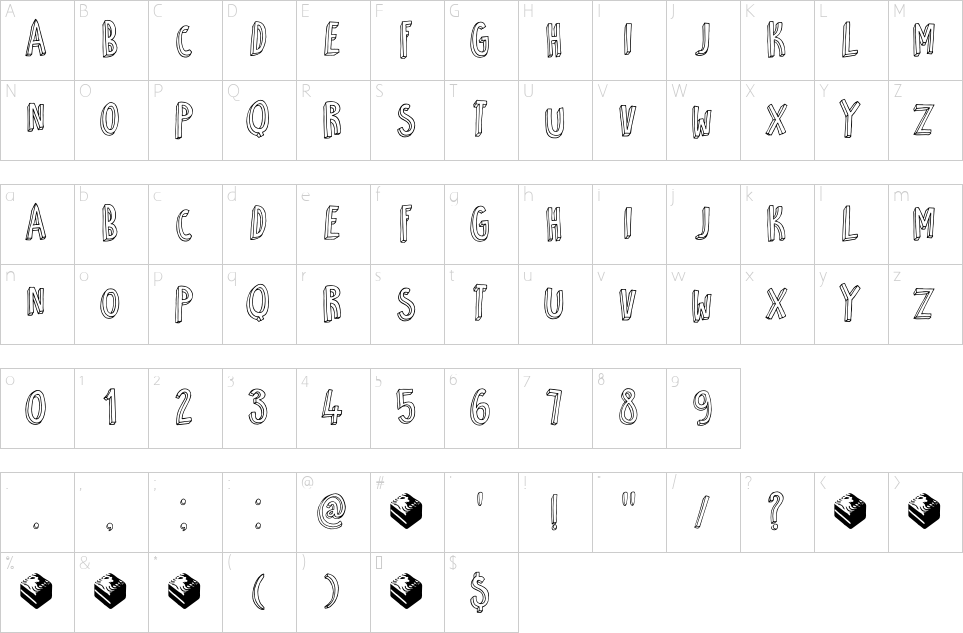
A DK Petit Four Font é uma deliciosa escolha para qualquer projeto gráfico que seja delicado e suave, especialmente se você estiver procurando por um estilo elegante que pode deixar seu trabalho brilhar ainda mais. Criada pelo designer Hanoded, esta fonte foi projetada pensando no equilíbrio entre personalidade e sofisticação. Com uma versão disponível tanto para Windows quanto para Mac, é simplesmente uma opção perfeita para quem busca um desenho de texto agradável e moderno. A DK Petit Four Font tem sido muito apreciada pelos designers devido à sua leveza e habilidade em se adaptar a várias situações de design, tornando-a uma fonte gráfica gratuita que merece ser testada. Com apenas 35,013 downloads, ela certamente já atingiu muitos artistas digitais apaixonados por estilos sutis. Se você está em busca de um toque suave e atraente para seus trabalhos, DK Petit Four Font é uma escolha inteligente.